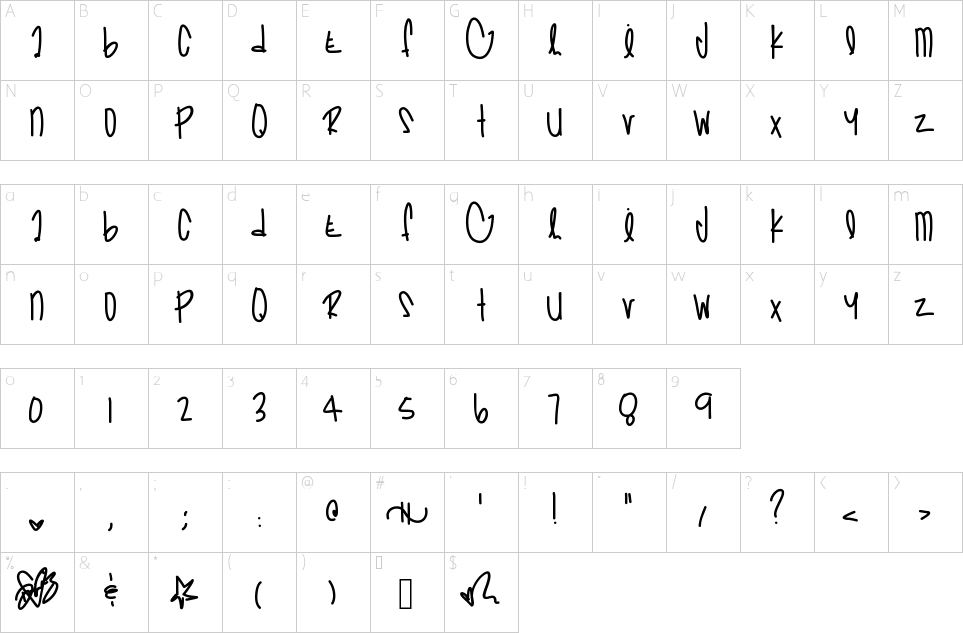
A fonte Pretty In Pinks é uma escolha irresistível para quem busca um toque de feminilidade e encanto em suas criações digitais. Desenvolvida por Des Gomez, essa fonte elegante traz uma paleta de cores e formas que remetem àqueles momentos de pureza e encanto. Confortável para uso em grandes fontes e legíveis nas pequenas, Pretty In Pinks é perfeita para estampas de roupas, ilustrações de personagens ou simplesmente para dar um toque de beleza ao seu trabalho. Atualmente, mais de 1.796 pessoas já desfrutaram do seu download, demonstrando seu valor tanto para designers gráficos quanto para estilistas de moda. Experimente agradar o seu público com essa fonte única e versátil.